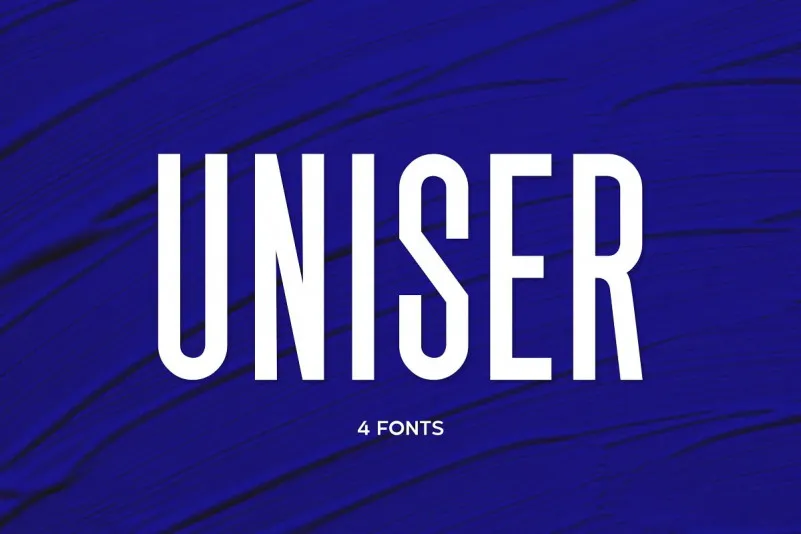
A Uniser Font é uma exuberante tipografia all caps, ideal para uso em elementos visuais modernos e agressivos. Inspirada nos logotipos poderosos das marcas famosas, especialmente aquelas relacionadas ao mundo dos calçados, esta fonte é perfeita para aplicações que exigem destaque, como materiais publicitários, roupas customizadas, embalagens e design de marca. Com quatro estilos distintos, a Uniser oferece uma gama de possibilidades para criar resultados satisfatórios. Suas linhas marcantes e forte identidade visual tornam-a perfeita não apenas para o desenvolvimento do logotipo, mas também para materiais de embalagem, camisetas personalizadas ou até mesmo a criação de posters impactantes. Ideal para designers que buscam um recurso visivo poderoso e contemporâneo.